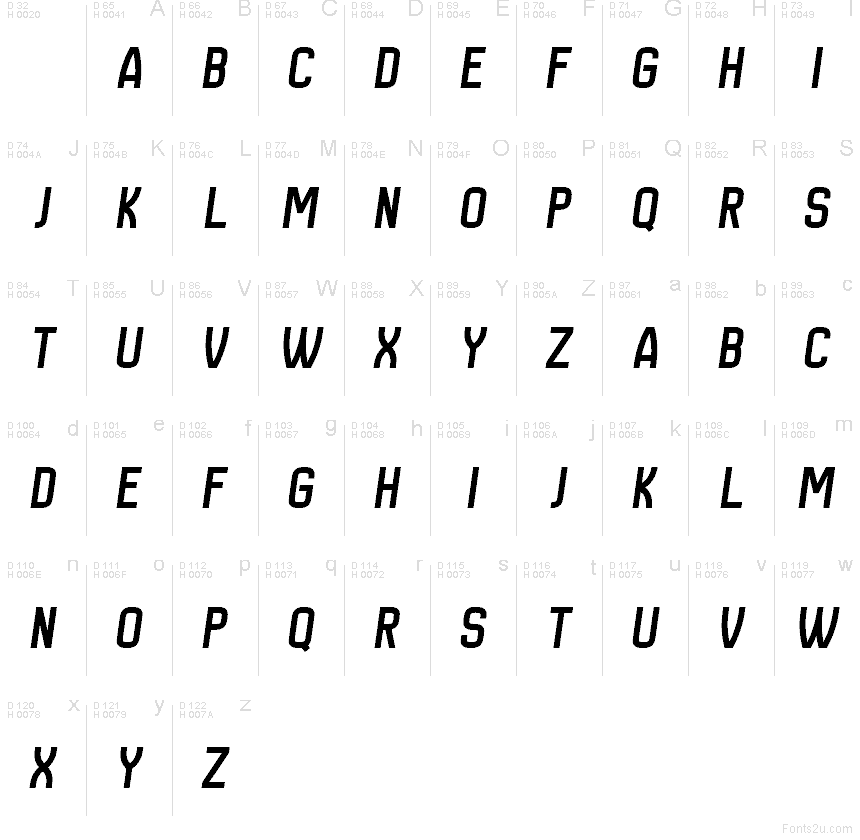
New Amsterdam Extravagant Italic von Vladimir Nikolic ist eine kostenlose, kursive serifenlose Schrift, die durch ihren markanten Schwung und die hohen, wie aus Papier geschnittenen Silhouetten besticht. Die wiederkehrenden diagonalen Schnitte und schmalen Vertikalen verleihen dem Schriftbild einen schnellen, plakativ-dynamischen Rhythmus, wodurch das Design eher unter Spannung steht als neutral zu wirken.
Diese Dynamik eignet sich hervorragend für Musikflyer, Sport-Branding, Eventplakate, Albumcover und Schlagzeilen, bei denen eine statische Sans-Serif zu flach wirken würde. Auch kurze Verpackungstexte und Social-Media-Grafiken profitieren von der steilen Neigung und den prägnanten Formen, die ohne zusätzliche Effekte eine starke Richtung vorgeben.